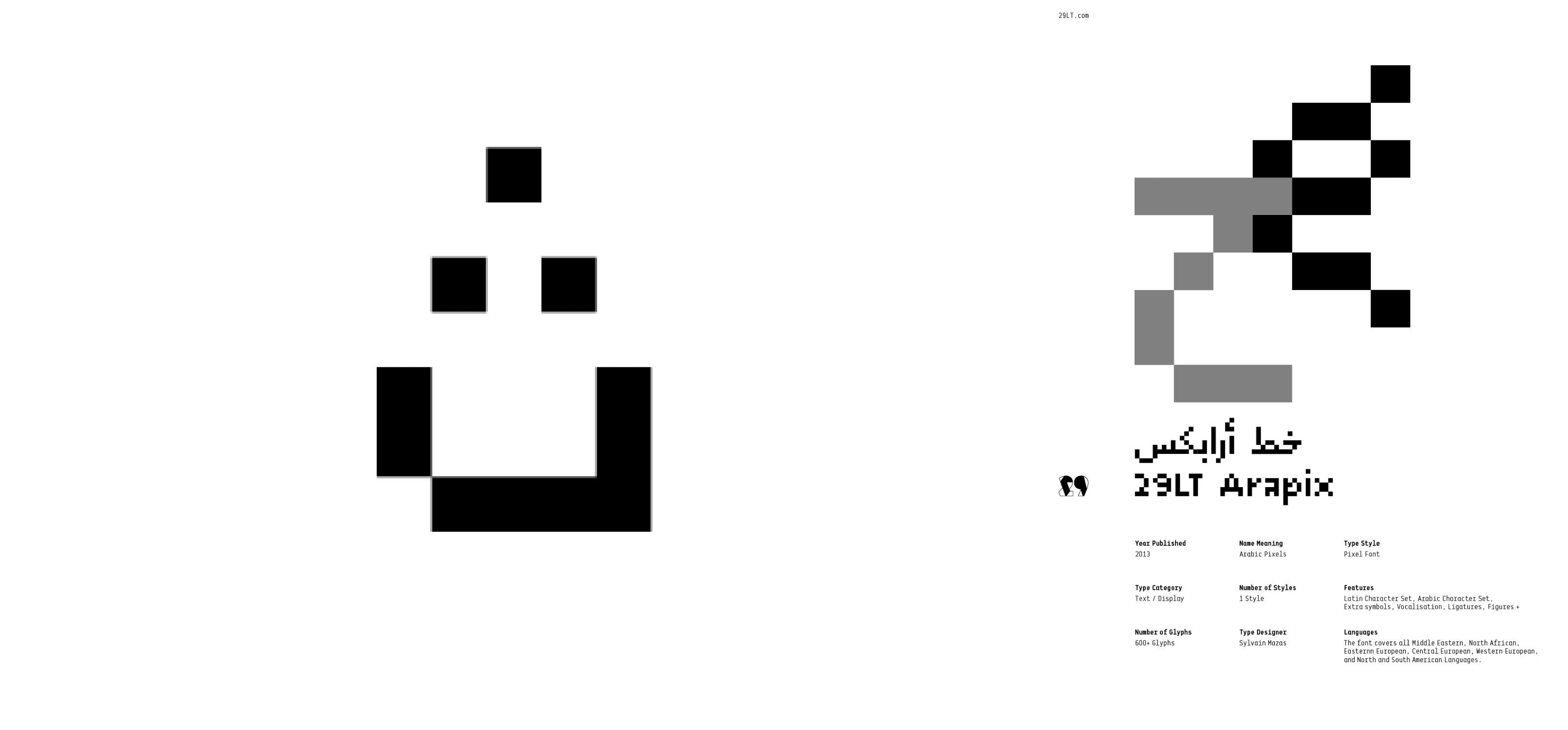
يقدّم خط Arapix من 29LT تجربة فريدة في التصميم الطباعي، تجمع بين الطابع البكسلي والتكوين الهندسي العصري. يتميز الخط بأشكاله الحادة والجريئة التي تعكس روحًا رقمية تتناسب مع المشاريع التكنولوجية، والأعمال الإبداعية، والتصميمات المستوحاة من فنون البكسل.
يدعم الخط اللغتين العربية واللاتينية، ويحتوي على مجموعة واسعة من المحارف والربطات التي تمنحه تنوعًا كبيرًا في الاستخدام. كما يتضمن خصائص تجعل منه خيارًا مثاليًا للعناوين، الملصقات، والمطبوعات المفاهيمية ذات الطابع المستقبلي أو التجريبي.